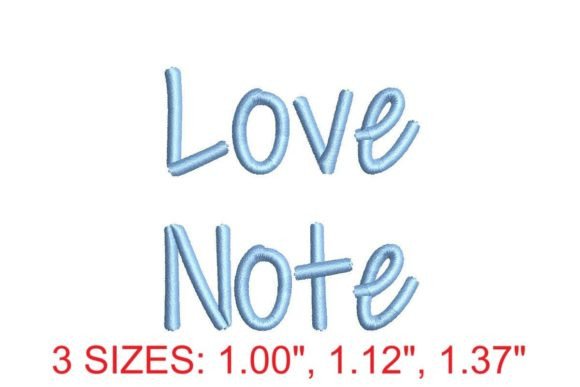
Love Note Embroidery Font
Nếu bạn đang tìm kiếm các tài nguyên chất lượng cao như Love Note Embroidery Font, gói cao cấp này là một lựa chọn tuyệt vời cho các dự án sáng tạo của bạn.
Được chế tác với độ chính xác cao, Love Note Embroidery Font cung cấp các vector sạch, kiểu chữ mượt mà và giấy phép thương mại để bạn yên tâm.
Cho dù bạn đang tạo sản phẩm POD (In theo yêu cầu), thiệp mời đám cưới hay đồ họa mạng xã hội, Love Note Embroidery Font đều là một sự lựa chọn lý tưởng.